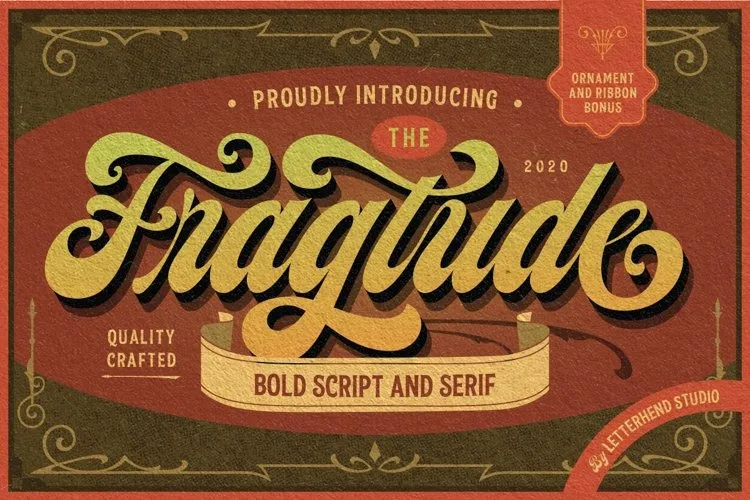
Esta é uma fonte vintage perfeita para diversas aplicações. Inspirada nas letras e sinalizações dos anos 40 e 50, ela evoca sentimentos nostálgicos que remetem às antigas décadas de ouro. Este item especial traz gratuitamente ornamentos e fitas em formato vetor. Estes elementos adicionais são ideais para adicionar um toque a mais de originalidade e charme ao seu projeto. Se você está procurando uma fonte vintage com personalidade, esta é uma ótima opção. A Fragtude Font oferece não apenas beleza visual, mas também o benefício adicional de ornamentações adicionais gratuitamente. Como designer ou criador de conteúdo que aprecia estilos retro e modernos ao mesmo tempo, este item certamente vale a pena considerar.